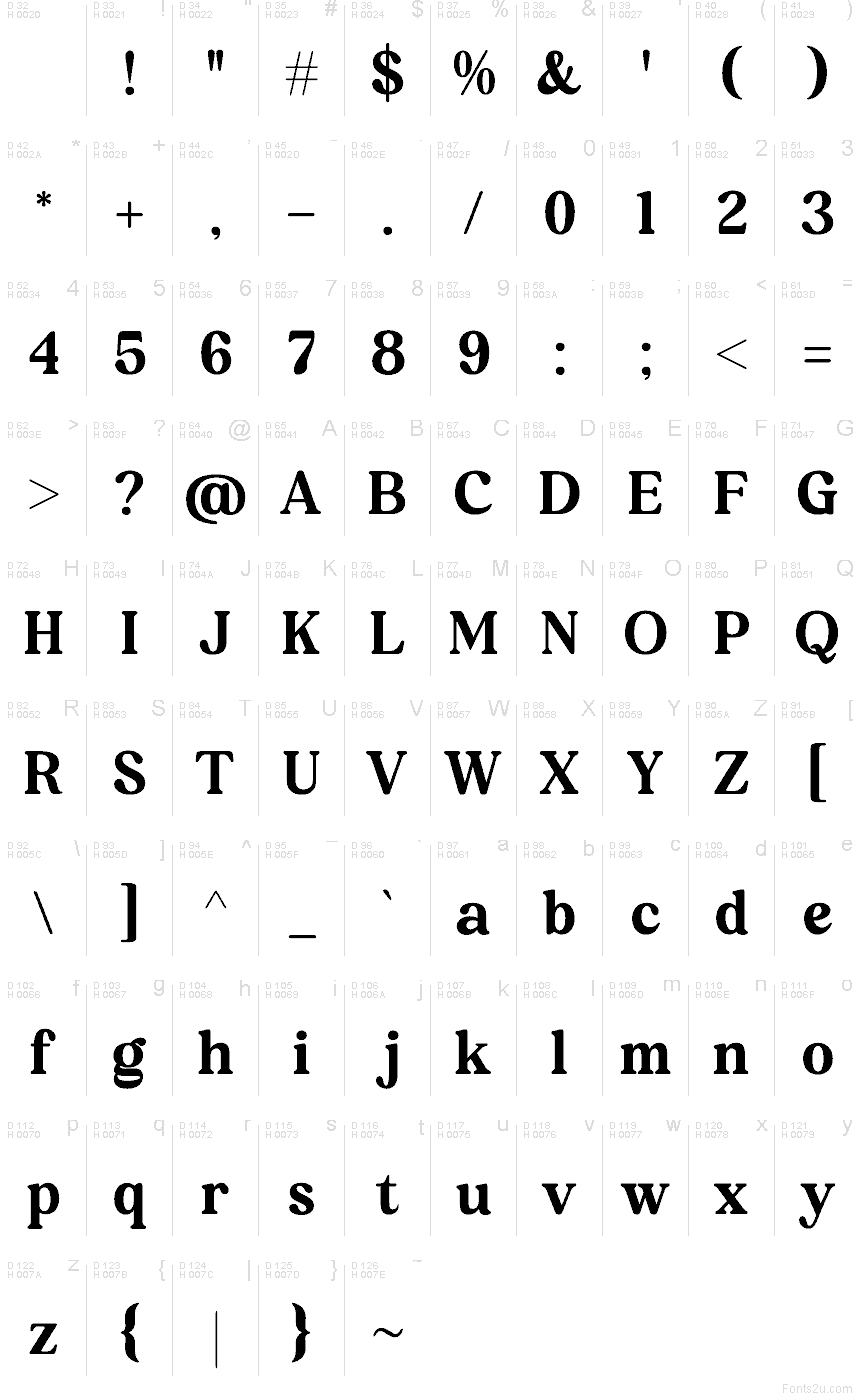
Hearty Sacred od TimelessType je bezplatné patkové písmo ve stylu vintage s jemným, pohádkovým nádechem. Písmena kombinují široké, měkké patky se zaoblenými křivkami a klasickým rytmem, takže písmo působí přátelsky a zakotveně, nikoliv ostře nebo formálně.
Přirozeně zapadne do designu obalů, brandingu kaváren, titulků plakátů, obálek knih a redakčních nadpisů, kde chcete klasický vzhled, který zůstává přístupný. Jako bezplatné písmo funguje skvěle také pro krátké nadpisy, citace a monogramy, protože tyto plné patky a velkorysé křivky dodávají i krátkým slovům bohatou a lákavou přítomnost.